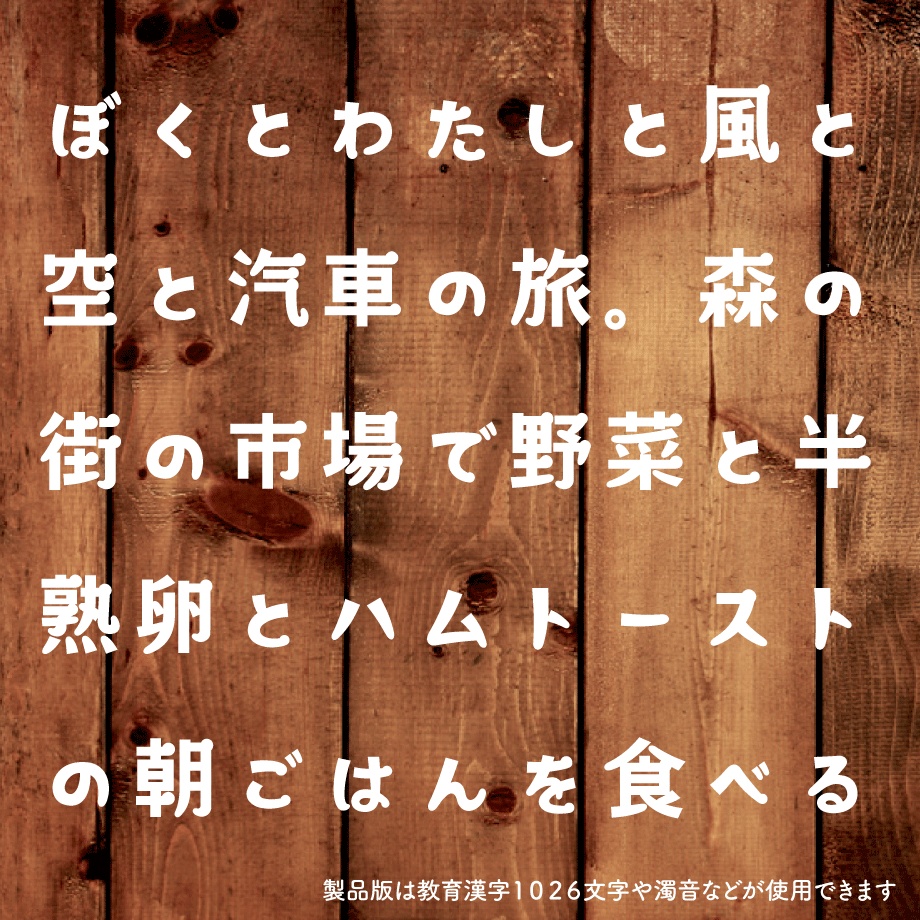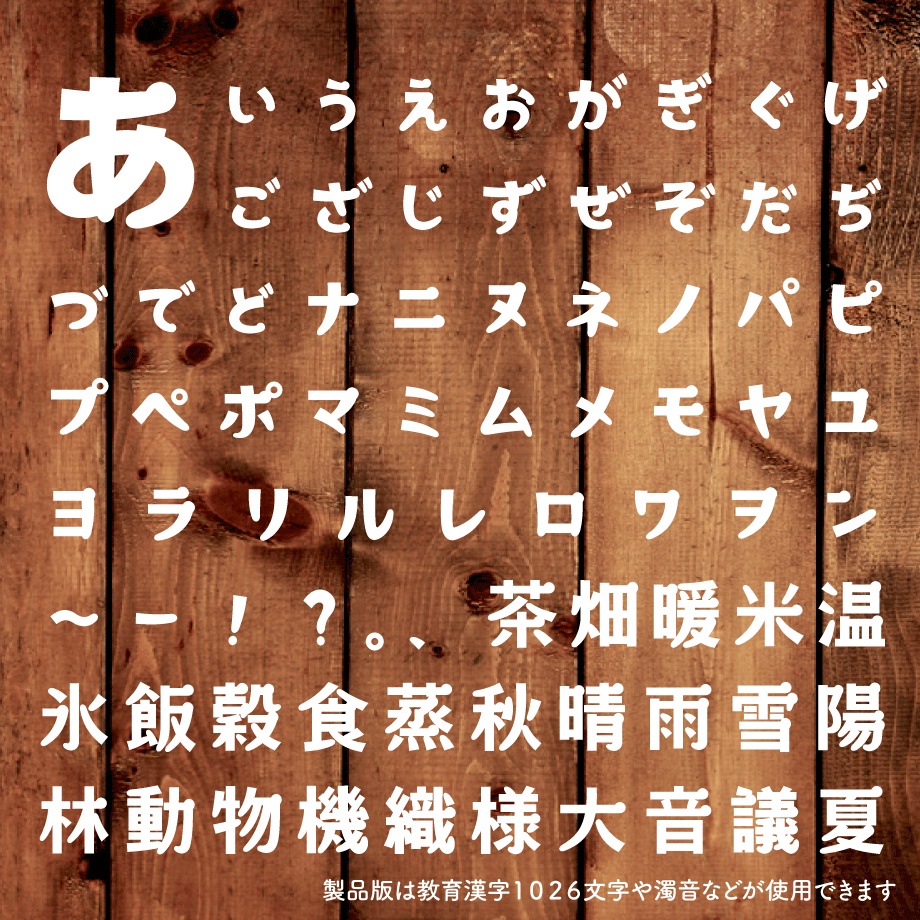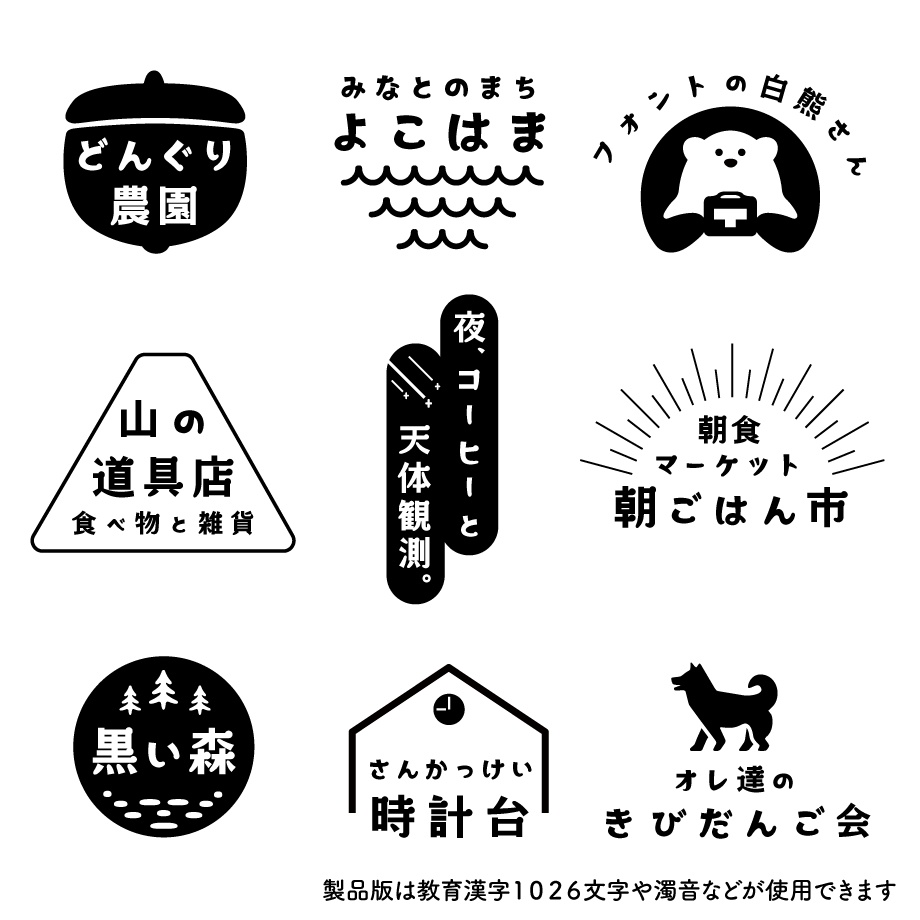
日本語フォント「森と湖の丸明朝」フリー版
日本語(和文)フォント「森と湖の丸明朝」は、アウトドアやカフェテリアなどでの使用をイメージした、素朴で温かな文字たちです。 ひらがなとカタカナ(清音のみ)、漢字(森、湖、丸、明、朝の5文字)を収録したお試し用の無料フォントデータです。 ● 仕様 フォントデータ形式:OpenType 収録字種:ひらがな(清音のみ)、カタカナ(清音のみ)、漢字(森、湖、丸、明、朝5文字)、約物(ー〜) ● ダウンロード販売ご利用に際して ダウンロードされた本フォントデータは、お客様ご自身の責任においてご利用ください。 本フォントデータは、WindowsおよびMacにインストールすると、対応するグラフィックソフトやワープロソフトなどで利用可能となります。また、OSやソフトウエアおよびそのバージョンによっては読み込めないことがあります。フォントのインストール方法やソフトウエア上での使用方法の詳細は、各解説書などでご確認の上ご利用ください。 ● 免責事項 本フォントデータの使用または使用に関連して、購入者の直接または間接的に生ずる一切の損害および第三者からなされる請求について、タイピングアートは一切責任を負担しません。 ● 使用範囲 商用での使用は出来ません。 ● 禁止事項 本フォントデータはサーバー等にアップロードして送信可能とする目的の使用は出来ません。 本フォントデータの改変、販売、頒布、バックアップ目的以外のコピーは許可されていません。 本フォントデータを使用して作成した成果物の著作権登録、意匠登録および商標登録など知的財産権の登録を行うことは許可されていません。